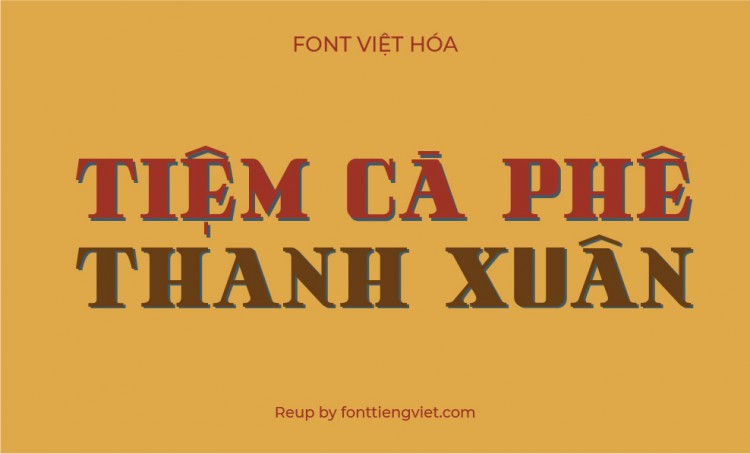
Font việt hóa LNTH PeterObscure ( Font vintage retro )
Trong thế giới thiết kế đồ họa hiện đại, việc tìm kiếm một bộ Font Chữ mang phong cách hoài cổ nhưng vẫn đảm bảo tính thẩm mỹ cao luôn là ưu tiên hàng đầu của các bạn học sinh và giáo viên. Font Miễn Phí xin giới thiệu bộ Font việt hóa LNTH PeterObscure ( Font vintage retro ), một sự lựa chọn hoàn hảo để thổi hồn vào các bài thuyết trình, báo tường hay những dự án thiết kế mang đậm màu sắc kỷ niệm. Với đường nét thanh thoát và cấu trúc ký tự độc đáo, bộ font này không chỉ đáp ứng tốt về mặt hiển thị mà còn tạo ra sự khác biệt rõ rệt cho các sản phẩm truyền thông học đường.
Đặc điểm nổi bật của Font việt hóa LNTH PeterObscure ( Font vintage retro )
Phong cách Retro độc đáo và tinh tế
Bộ Font việt hóa LNTH PeterObscure ( Font vintage retro ) mang trong mình vẻ đẹp của những thập niên cũ với các đường nét bo tròn và chân chữ cách điệu. Đây là loại font chữ cực kỳ phù hợp cho các tiêu đề lớn, bìa sách hoặc trang trí thiệp mời. Sự kết hợp giữa nét cổ điển và sự tinh tế hiện đại giúp người dùng dễ dàng truyền tải thông điệp một cách ấn tượng.
Tối ưu hóa tiếng Việt và tính ứng dụng cao
Điểm cộng lớn nhất của phiên bản này chính là việc được việt hóa hoàn chỉnh, không gây lỗi dấu khi soạn thảo trên các phần mềm phổ biến. Điều này giúp các bạn học sinh dễ dàng thực hiện các bài tập thiết kế mà không lo về vấn đề kỹ thuật. Bộ font này thường được sử dụng trong các bối cảnh cần sự ấm cúng, thân thuộc và mang tính giáo dục cao.
Kết luận về bộ Font việt hóa LNTH PeterObscure ( Font vintage retro )
Sử dụng Font việt hóa LNTH PeterObscure ( Font vintage retro ) sẽ giúp các dự án của bạn trở nên chuyên nghiệp và bắt mắt hơn bao giờ hết. Nếu bạn đang tìm kiếm giải pháp sáng tạo tại Font Miễn Phí, Font Việt Hóa, Font việt hóa LNTH PeterObscure ( Font vintage retro ), đừng bỏ lỡ cơ hội sở hữu bộ font tuyệt đẹp này để nâng tầm các tác phẩm thiết kế học đường của mình ngay hôm nay.